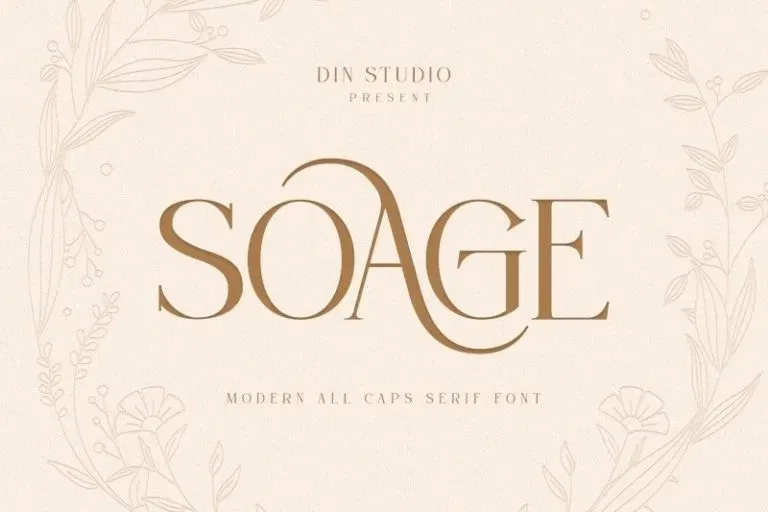
Soage Font – Download Grátis
A Soage Font é uma elegante escolha para projetos profissionais. Ela traz elementos serifados que se adequam perfeitamente a títulos e textos mais formais, oferecendo um visual arredondado e sofisticado. Com muitas alternativas disponíveis, ela se destaca em qualquer projeto de branding, permitindo-lhe adaptar seu design conforme necessário. A Soage é especialmente útil para aplicações como impressão, onde a qualidade do texto é fundamental, mas também combina perfeitamente com projetos criados especificamente para a web. Seja para criar uma identidade visual unificada ou simplesmente personalizar suas mensagens de casamento e citações, Soage está aqui para ajudar em sua necessidade de design gráfico. Este font é uma ótima escolha para qualquer designer que busca um equilíbrio perfeito entre modernismo e elegância.